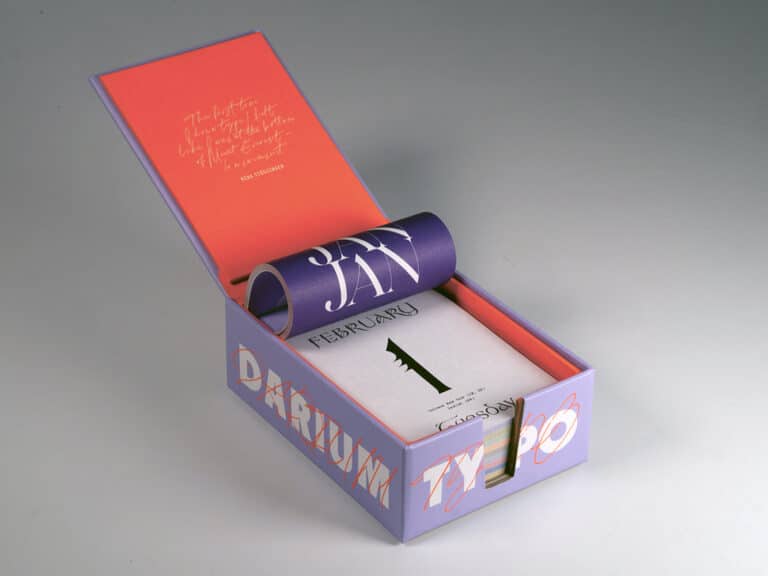
Typodarium 2022: Die tägliche Dosis Typografie
248 Typedesigner aus 35 Ländern zeigen frische Fonts – einen für jeden Tag.
Der Klassiker unter den Type-Kalendern bringt Schrift-Inspiration Tag für Tag. Brotschriften und Ausgefallenes, langlebige Leseschriften und edle Zierschriften. Für jeden Geschmack und jede Gelegenheit ist was dabei. So wird die robuste Box, in der das Typodarium verpackt ist, zum Schatzkästchen für Kreative, die Schrift lieben.
Weil Handgemachtes angesagt ist, zeigt das Typodarium 2022 an Sonn- und Feiertagen Schriften, die mit Schere und Stiften, mit Klebeband und Stempeln entstanden sind. Sonntags darf es unperfekt sein, etwas rau mit Ecken und Kanten.